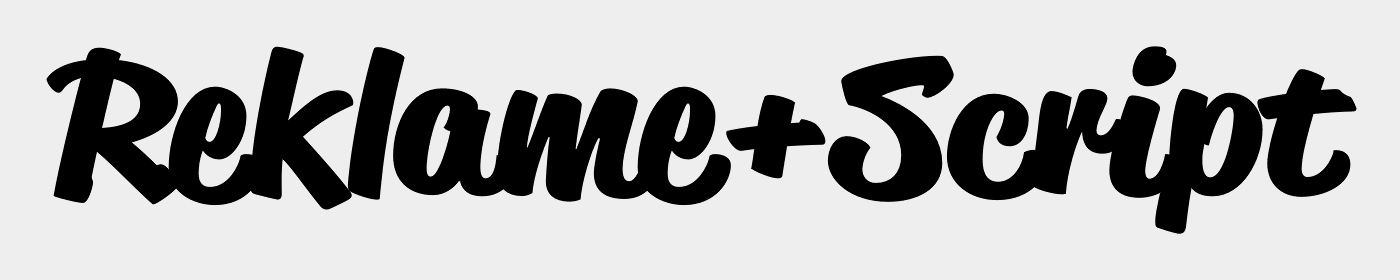
Suche einen Font im Stil von FF Market
jedoch mit automatischen Alternativen für doppelte Zeichen
Unterschiedliche Stärken wären toll, generell aber nicht dünner als der reguläre Schnitt der FF Market. FF Mister K ist ganz nett, wenn euch etwas zu verspielt und leider auch etwas zu fein. Amadeo geht in die richtige Richtung, jedoch sind die Alternates nur über zusätzliche Fonts zu erreichen. Suomi Hand etwas zu fein und schon fast zuviel Kugelschreiber als Marker.
Hat noch jemand eine Idee?
Probiere:
Enamel Brush von Typodermic, hat einige Alternativen für doppelte Glyphen (nicht für alle).
Holly Script von Estudio Calderon, hat auch einige Alternativen.
Meine Suche basierte auf dem MyFonts-Algorithmus »brush + OT feature: Stylistic Alternates«. Möglicherweise gibt es für dein Anliegen eine bessere OT-Formulierung …
Die regulare Reklame Script geht in die richtige Richtung, die anderen Schnitte sind zu fett.
Quick Marker/Brush ist hübsch aber zu fett und teilweise zu ausgefallen.
Rollerscript würde ganz gut passen, wäre sie nur ein Hieb fetter, werde Sie aber nochmal genauer testen.
Enamel Brush (die habe ich vor Jahren schon lizensiert aber nie bewusst genutzt) und Holly Script sind zu brushig.
Ich benötige Sie eher für kleinteilige Beschriftungen, keine Schaufenster oder Poster.
Mir ist gerade noch die Walmer Marker von Typolar eingefallen, die ist mir aber auch schon zu fancy und hat auch keine alternativen Zeichen.